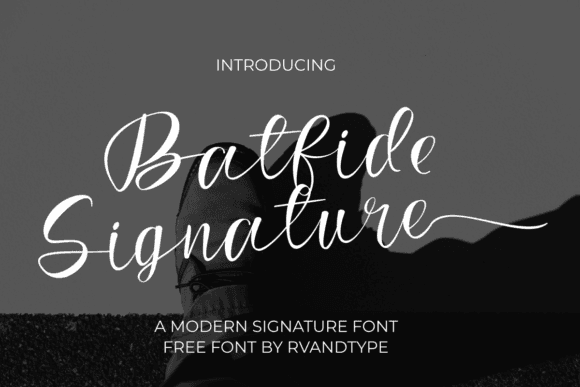
Fuente Batfide Signature para branding femenino y gráficos para redes sociales
Fuente de firma Batfide
Batfide Signature es una fuente caligráfica encantadora y delicada que irradia elegancia y clase. Esta fuente está codificada en PUA , lo que significa que puedes acceder fácilmente a todos sus increíbles glifos y ligaduras.
- Fuente de escritura elegante y con clase